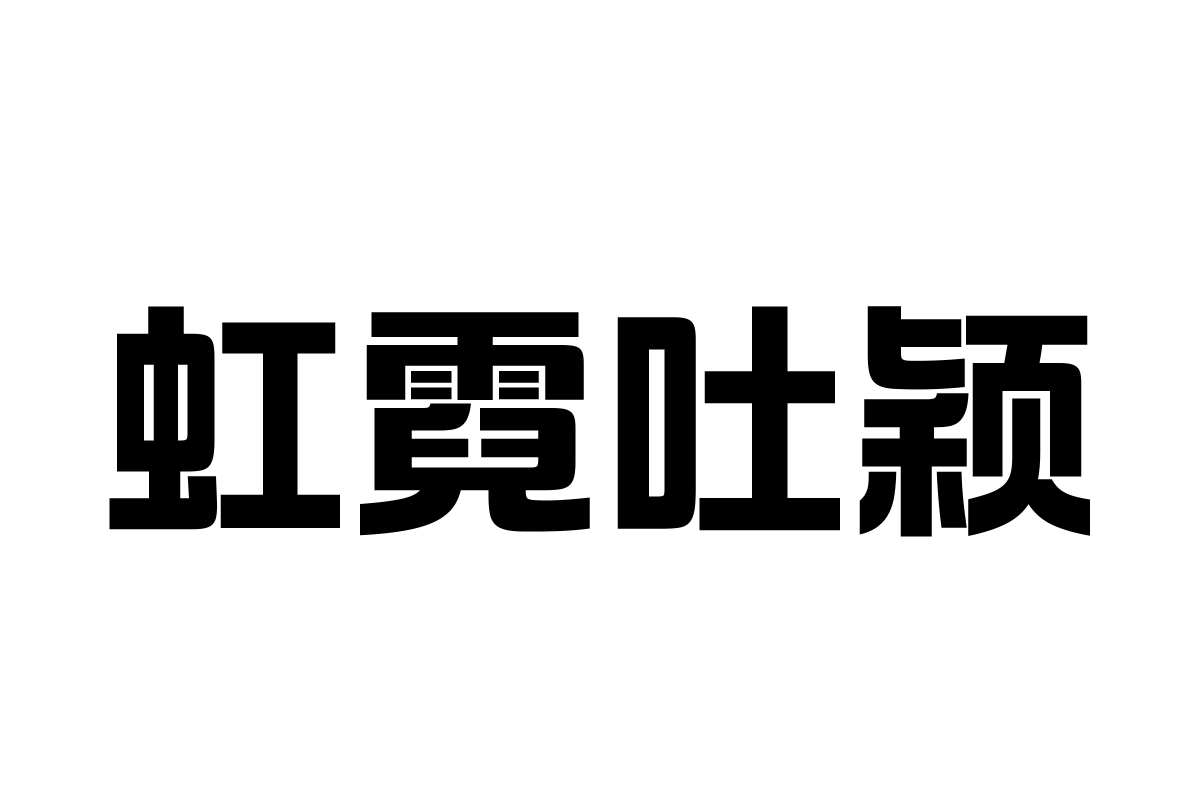
汉仪风尚黑85w是一款现代而优雅的中文字体,适用于各种印刷品和数字媒体。这款字体具有独特的风格和设计,给人一种时尚、简约而又不失个性的感觉。它由85个字符组成,每个字符都有不同的笔画和形状,使得整个字体看起来更加丰富和有趣。
汉仪风尚黑85w的特点在于它的简洁性和易读性。它的笔画清晰明了,没有多余的装饰,使得阅读起来更加轻松。同时,它的字形也具有一定的美感,适合用于标题、正文等需要突出显示的部分。
此外,汉仪风尚黑85w还具有很好的可读性。它的字形大小适中,既不过于紧凑也不过于宽松,使得在不同大小的屏幕上都能保持良好的视觉效果。无论是在小尺寸的手机上还是在大尺寸的屏幕上,汉仪风尚黑85w都能展现出其独特的魅力。
总的来说,汉仪风尚黑85w是一款非常适合现代设计需求的中文字体。它的简洁、易读和可读性等特点使其成为了许多设计师的首选。无论是用于印刷还是数字媒体,汉仪风尚黑85w都能为你的作品增添一份独特的魅力。